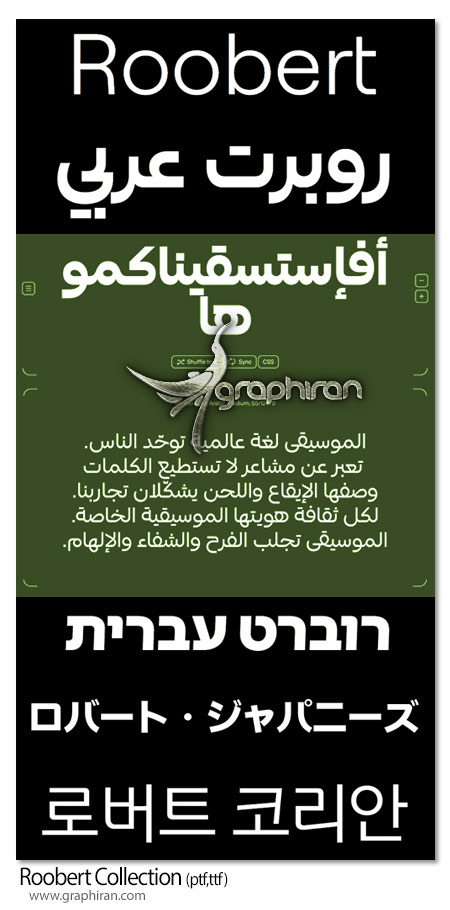
فونت انگلیسی و عربی روبرتو Roobert Fonts Collection مجموعهای حرفهای از فونتهای سنسریف هندسی با طراحی مینیمال و ساختاری تمیز است. این خانواده فونت با ساختار Mono-linear، انتهای افقی و عمودی و اتصالهای نرم روی حروف طراحی شده و از زبانها و سیستمهای نوشتاری متنوعی پشتیبانی میکند.
Roobert در ابتدا بهعنوان یک فونت سفارشی برای Moogfest 2017 طراحی شد و الهام اصلی آن از لوگوتایپ Moog گرفته شده است. این مجموعه علاوه بر حروف لاتین و اروپای مرکزی، از زبانهای یونانی و سیریلیک و همچنین عربی، عبری، ژاپنی و کرهای پشتیبانی میکند.
نسخه Roobert Latin شامل ۳ خانواده، ۱۸ وزن و ۳۶ استایل است. نسخههای عربی، عبری، کرهای و ژاپنی نیز مجموعههای اختصاصی خود را با وزنها و استایلهای متنوع ارائه میکنند.
- شامل ۵ خانواده فونت
- شامل ۹۰ استایل
- شامل ۵ فونت متغیر
- شامل ۵ اسکریپت
- پشتیبانی از Latin
- پشتیبانی از Cyrillic
- پشتیبانی از Greek
- پشتیبانی از Arabic
- پشتیبانی از Hebrew
- پشتیبانی از Korean
- پشتیبانی از Japanese
- شامل ۱۸ وزن و ۳۶ استایل در خانواده Roobert Latin
- شامل ۶ وزن و ۶ استایل در خانواده Roobert Arabic
- شامل ۱۸ وزن و ۳۶ استایل در خانواده Roobert Hebrew
- شامل ۶ وزن و ۶ استایل در خانواده Roobert Korean
- شامل ۶ وزن و ۶ استایل در خانواده Roobert Japanese